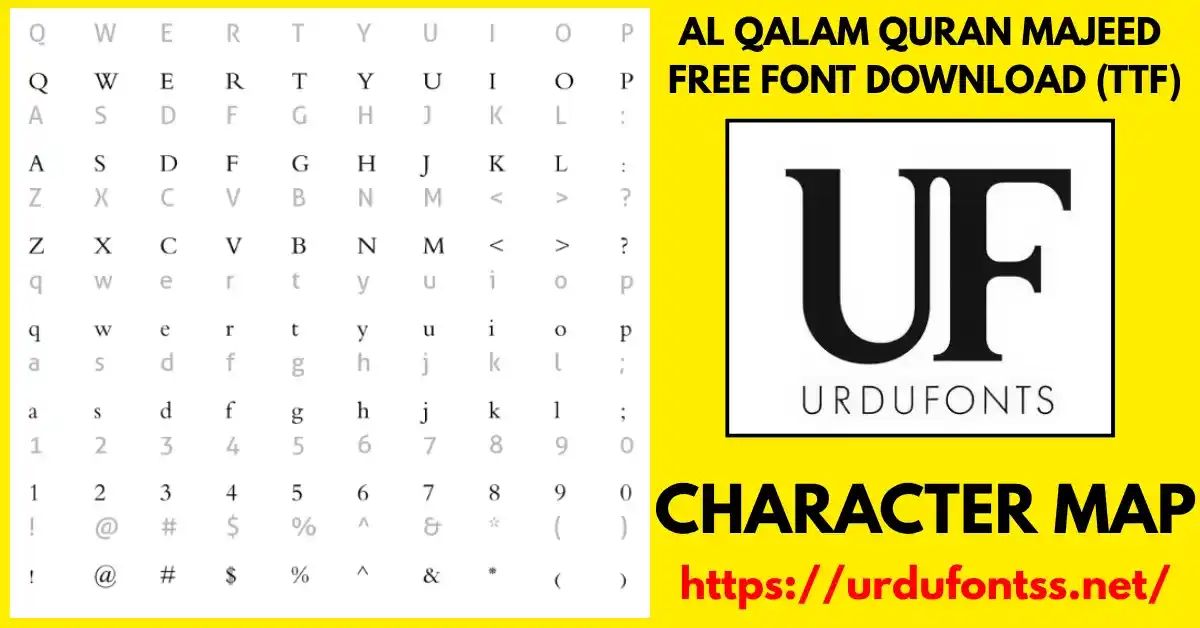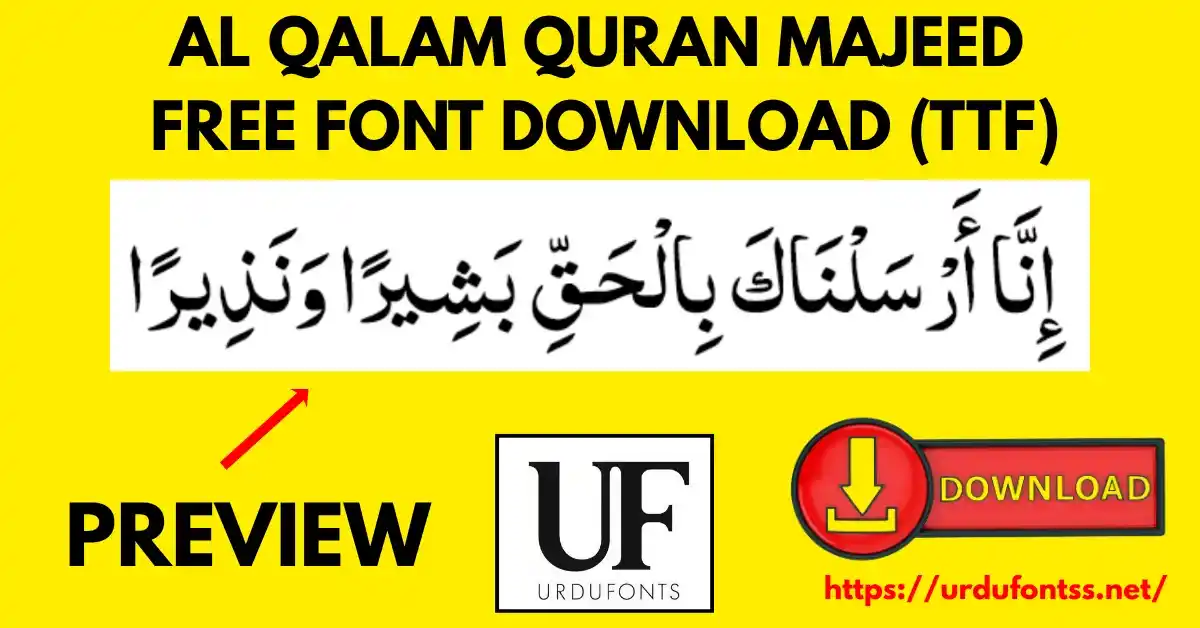
Dosto kya aap Al Qalam Quran Majeed Arabic font dhundh rahe hain? Agar aap Quranic text, Islamic content, ya Arabic typography ke liye professional Arabic Naskh font chahte hain to yeh guide aap ke liye hai.
Al Qalam Quran Majeed ek Regular TrueType Arabic font hai. Yeh font specially Arabic Naskh style mein design kiya gaya hai jo Quranic text aur Islamic publications ke liye bohat popular hai. Arabic fonts ki duniya mein yeh font ek trusted name hai.
What is Al Qalam Quran Majeed Arabic Font?
Al Qalam Quran Majeed ek Regular TrueType Arabic font hai. Yeh Arabic Naskh style mein structured hai jo Quranic text aur Islamic publications ke liye design kiya gaya hai. Arabic fonts mein yeh apni cleanliness aur readability ke liye jana jata hai.
Yeh Arabic font un designers aur bloggers mein widely popular hai jo Quranic content aur Islamic typography par kaam karte hain. Arabic Naskh font hone ki wajah se yeh Quranic text ke liye best Arabic font hai.
Designer of Al Qalam Quran Majeed Arabic Font
Al Qalam Quran Majeed Arabic font ko design kiya gaya hai:
| Designer | Company |
|---|---|
| Muhammad Zuhair Ruhani Bazi | Adobe Fonts |
| Robert Slimbach | Adobe Fonts |
Yeh Arabic font Adobe Fonts platform par structure kiya gaya hai. Muhammad Zuhair Ruhani Bazi aur Robert Slimbach ne is Arabic Naskh style font ko design kiya jo Quranic text ke liye best Arabic font hai.
Robert Slimbach ek renowned type designer hain jo Adobe mein kaam karte hain. Unhone bohat se famous Arabic fonts aur Latin fonts design kiye hain.
Muhammad Zuhair Ruhani Bazi Arabic typography mein expert hain aur unhone kai professional Arabic fonts design kiye hain.
Al Qalam Quran Majeed vs Other Arabic Fonts
Al Qalam Quran Majeed ko doosre Arabic fonts se compare karte hain:
| Feature | Al Qalam Quran Majeed | Other Arabic Fonts |
|---|---|---|
| Style | Arabic Naskh | Traditional Naskh, Kufi, Thuluth |
| Best For | Quranic text | General Arabic text |
| Designer | Adobe Fonts | Various |
Yeh Arabic font kyun choose karein:
- Clean Arabic Naskh style for Quranic text
- Professional design by Adobe designers
- Trusted Arabic font for Islamic publications
Arabic Naskh Style – What Makes This Font Special?
Arabic Naskh style Arabic fonts ki ek important category hai. Al Qalam Quran Majeed isi style mein design kiya gaya hai.
Why Arabic Naskh Style is Important:
| Feature | Benefit |
|---|---|
| Clear and Readable | Quranic text easily padha ja sakta hai |
| Simple Letter Forms | No unnecessary complexity |
| Professional Look | Islamic publications ke liye best |
| Widely Accepted | Quran printing mein standard style |
Arabic Naskh fonts ko specifically Quranic text aur Islamic books ke liye design kiya jata hai. Al Qalam Quran Majeed is style ka ek best example hai.
Where Is Al Qalam Quran Majeed Arabic Font Commonly Used?
Al Qalam Quran Majeed Arabic font bohat versatile hai aur yeh jagah use hota hai:
1. Quranic Text Publications
- Quran printing (Mushaf)
- Islamic books
- Religious publications
- Tafseer books
2. Islamic Content Creation
- Islamic YouTube videos
- Islamic posts for social media